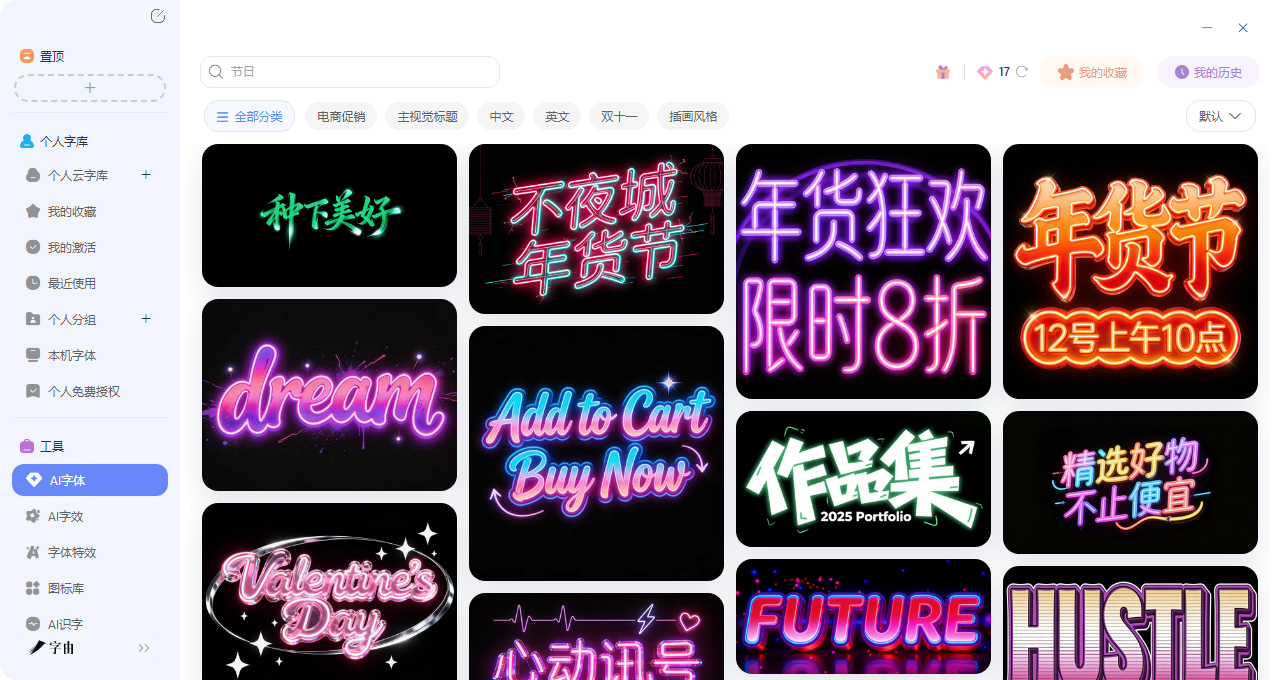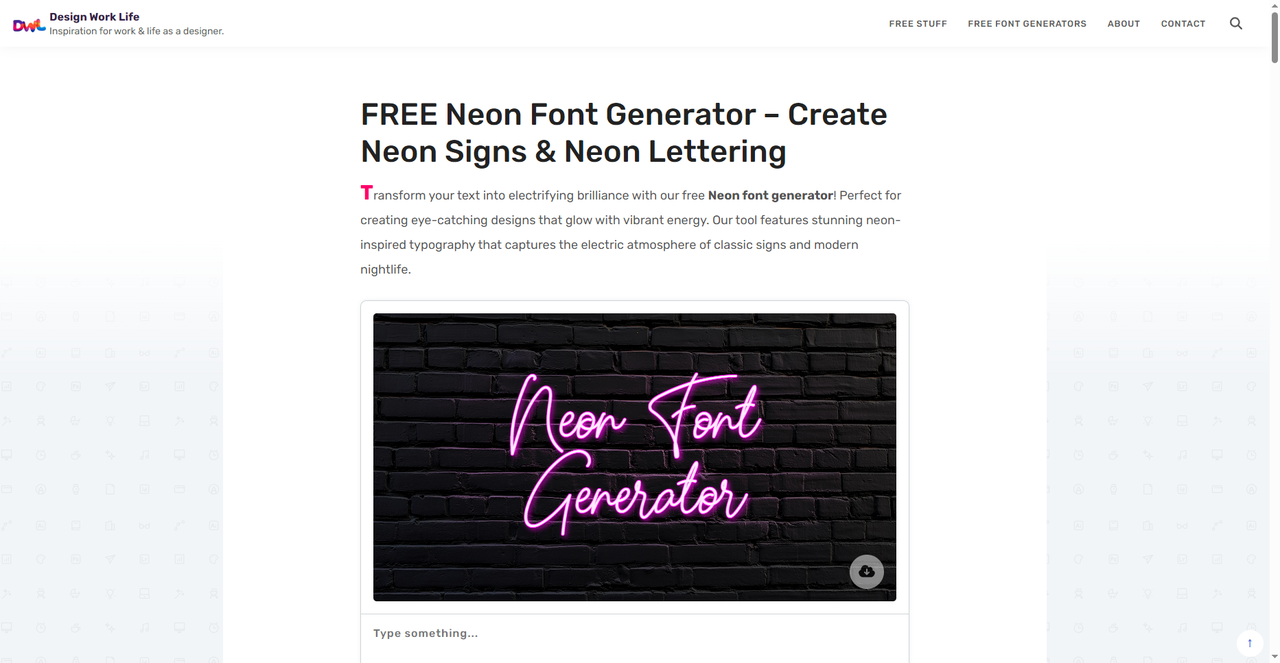
不会做霓虹灯字?这几个AI工具分分钟搞定
霓虹灯这个元素实在是太常见了,不论是深夜城市里的招牌灯,比如红色的“BAR”、蓝色的“HOTEL”、粉紫色的“OPEN”,还是在游戏里你都能够看到这个元素,这种自带氛围感的文字,放在海报、视频封面、游戏标题里,可以直接吸引人的注意力。那么在今天,霓虹灯的字体制作已经不再需要费时费力地去设计、调整了,因为有了霓虹灯字体AI生成工具的出现,这一切都会变得很简单。那么今天我会在本篇介绍5 个好用的霓虹灯字体AI生成工具,上手以后你会发现十分简单,那么一起来看看吧!
第一个要推荐的霓虹灯字体AI生成工具是字由,字由虽然是字体库,但是里面也有着不少实用的AI工具,其中就包括了AI字体,专门用来生成各种风格的艺术字,霓虹灯效果当然也在其中。下面我会按步骤来拆分如何快速用字由来免费生成霓虹灯字体:
第一步:打开字由客户端,左侧导航栏找到【工具】→【AI字体】,或者从首页【字体工具】→【AI工具】进入。这个功能内置了大量艺术字模板,涵盖电商风、国潮风、科技感,以及我们需要的霓虹灯文字生成模板。
第二步:进入AI字体页面后,在搜索框里输入“霓虹”“发光”“霓虹灯”“光效”等关键词,系统会自动筛选出所有带霓虹质感的模板。
第三步:搜索结果会展示各种霓虹风格的预览图,比如:
- 霓虹灯管效果(带玻璃管质感,像真实的招牌灯)
- 彩色渐变发光(多种颜色过渡,适合赛博朋克风)
- 柔和光晕发光(边缘有朦胧光晕,温柔梦幻)
- 闪烁动画效果(动态霓虹字,适合视频标题)
- 故障风霓虹(带数字故障纹理,适合电子音乐海报)
第四步:点击选中的模板,进入编辑页面。在输入框里填你想要生成霓虹效果的文字(比如“夜生活”“ROCK”“LOVE”)
第五步:确认文案后,点“立即生成”,等20-30秒左右,系统就会输出设计好的霓虹艺术字图片。生成后可以预览效果,如果不喜欢的话可以选择再换。
第六步:生成满意后,点击下载。
这样就是在字由里下载霓虹灯字体的全部步骤了,整个流程不会超过三分钟。当然如果你比较精挑细选的话可能会额外花费一些时间,字由比较适合那些想要快速出图的用户,就算是下载下来的内容你还有地方不满意可以自己慢慢调试,这总比自己从零开始设计要好得多了!
2、FREE Neon Font Generator
这是一个非常直观的在线工具,专为霓虹灯文字生成设计。打开网页,中间就是一个输入框,你键入文字,右边立刻生成霓虹效果。界面非常清爽,没有花里胡哨的东西。这个工具虽然我只展示了字体,但是下面它还有很多实用的调节功能:
- 文字输入:支持中文和英文,直接打字就能预览。
- 参数调节:可以调整字体大小(最大123px)、画布尺寸(420px)、行高、字间距、文字旋转角度。
- 颜色控制:可以选择字体颜色、轮廓(描边距离)、背景色和阴影,自由组合出想要的霓虹色调。
这个也比较适合那些想要快速出图的设计师,而且哪怕你是零基础也可以你直接上手。
3、 Neon fonts
这个网站虽然不像上面两个是直接输入文字然后得到特效字体,但是它专门收集了各种霓虹灯字体。首页展示了多款风格不同的霓虹字体。
- Neon Beats:粗壮有力,适合电子音乐海报
- Popsa Spark:细长优雅,带一点闪烁感
- Bycore Ultra:未来感十足,适合科技主题
- Lumin Drop:圆润可爱,像糖果霓虹
每一款都标注了名称,你可以直接下载,对于那些不想要AI字效只想要字体的设计师们来说是绝对友好的。
4、Neon Font Generator
这个是一款功能丰富的在线你霓虹字体在线生成器,这可以说是霓虹灯字体AI生成的进阶版,因为在这里你可以现在调整关于字体的所有事项,比如说:
- 精细调节:可以设置字体、字重、字间距、行高、文本对齐等。
- 样式效果:提供“Neon Light”“Neon Glow”等预设,还能单独调整阴影、边框、背景。
- 颜色和谐:支持启用Color Harmony,自动搭配霓虹色系。
- 保存预设:可以保存自己的设计预设,下次直接调用。
- 分享链接:生成后可获得一个可分享的设计链接,方便团队协作。
如此之多的功能可以说直接一步到位了。
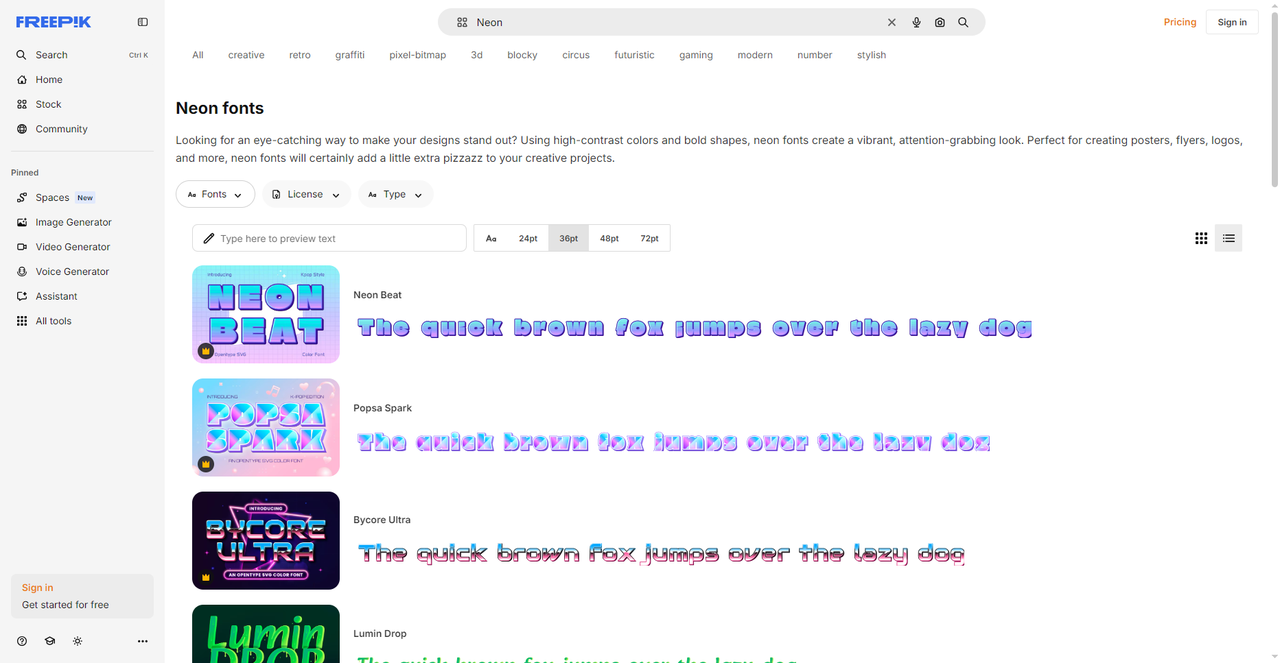
5、TextStudio
这个网站也是我们的老朋友了,我基本在所有AI字体工具里面都会提到它,虽然模板之类的都有点老,但是它的资源丰富程度绝对是无需质疑的,当然这里面也包括了霓虹灯字体,如果你需要做游戏标题、电影片头、品牌Logo那种有立体感的霓虹字,这个工具非常合适。